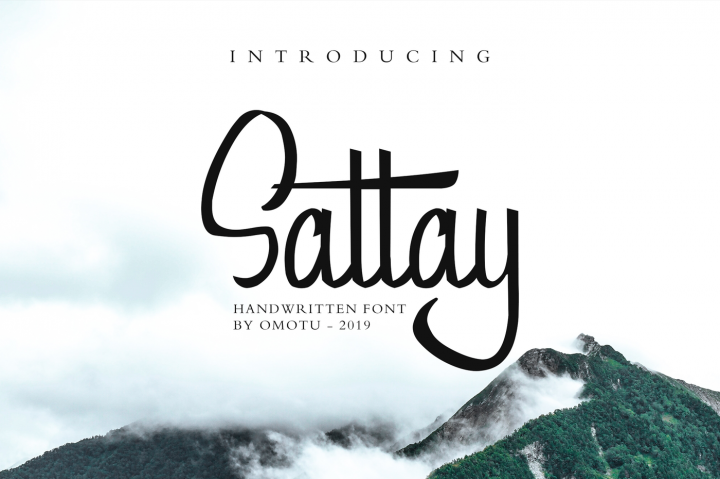
Sattay Script Font – Download Grátis
Olá! Comece a nova semana com uma tipografia escrita à mão e estilo calligrafia. Introduzimos Sattay Font. Designado por Omotu, Sattay é um novo script moderno e fresco. Seu estilo mistura escrita à mão e estilo de fonte, o que dá ao fonte um ar elegante, sofisticado e perfeito para projetos que precisam do sabor da escrita à mão. Sattay se encaixa perfeitamente em fotografias, marca-d água, postagens nas redes sociais, anúncios, logotipos & marcação, cartas de convite, designs de produto, rótulos, material de correspondência, decoração para casamento e embalagem de produto. Além disso, ele é ideal para eventos especiais ou qualquer coisa que precise do sabor da escrita à mão.